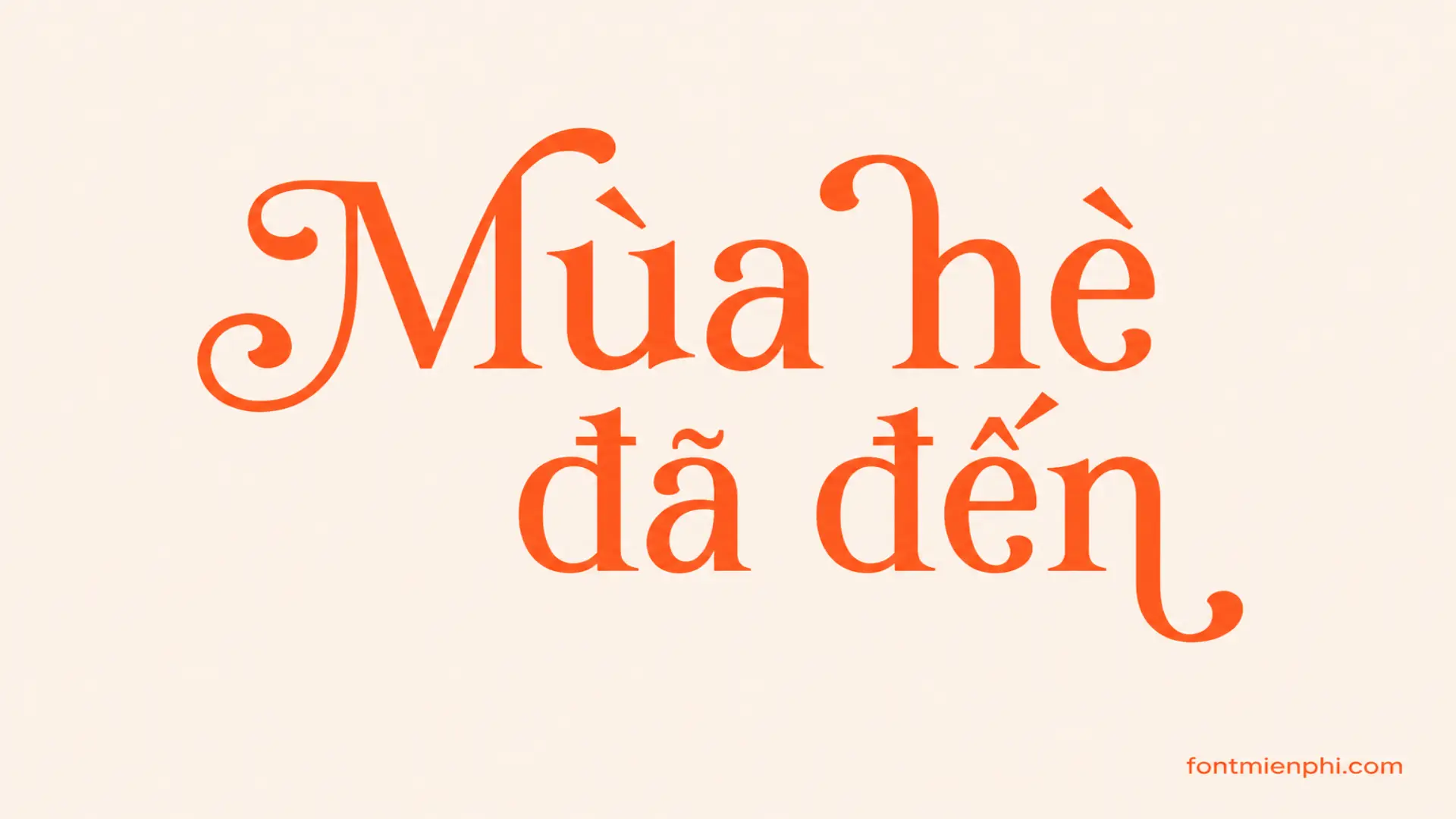
Font Việt hóa 1FTV VIP History Nineties
Tải Font Việt Hóa 1FTV VIP History Nineties – Trở Về Thập Niên 90 Cùng Thiết Kế Đậm Chất Retro
Phong cách Retro/Vintage chưa bao giờ là lỗi thời trong thế giới đồ họa. Nếu bạn đang tìm kiếm một “cỗ máy thời gian” để đưa các tác phẩm của mình quay trở lại không gian hoài niệm, cổ điển đầy chất thơ, thì Font Việt hóa 1FTV VIP History Nineties chính là tấm vé hoàn hảo nhất.
1. Tổng quan về Font 1FTV VIP History Nineties
History Nineties mang trong mình hơi thở của những năm 1990 – thập kỷ giao thoa giữa nét văn hóa mộc mạc và sự bùng nổ của nghệ thuật đại chúng (Pop Art). Cấu trúc của phông chữ này là sự hòa quyện tuyệt vời giữa các đường lượn sóng mềm mại, form chữ dày dặn và những nét cắt dứt khoát mang hơi hướng của các biển hiệu quảng cáo xưa cũ.
Đặc biệt, phiên bản Việt hóa VIP từ 1FTV đã khắc phục hoàn toàn điểm yếu của các font nước ngoài khi gõ tiếng Việt. Toàn bộ các dấu câu (hỏi, ngã, nặng, sắc, huyền) và các ký tự đặc thù (ă, â, đ, ê, ô, ơ, ư) đều được tinh chỉnh thủ công. Dấu câu được đặt ở tỷ lệ hoàn hảo, không làm vỡ bố cục gốc, giúp tổng thể Typography trở nên mượt mà và chuyên nghiệp.
2. Vì sao History Nineties là “Must-have Font” của Designer?
• Đậm đà phong cách Retro: Chỉ cần gõ một dòng text, ấn phẩm của bạn đã lập tức toát lên vẻ hoài cổ, lãng mạn mà không cần lạm dụng quá nhiều hiệu ứng hình ảnh (texture).
• Dễ đọc, nổi bật: Dù mang phong cách Vintage, các ký tự vẫn giữ được sự rõ ràng, tách bạch, đảm bảo khả năng truyền đạt thông điệp xuất sắc (Legibility).
3. Gợi ý ứng dụng Font History Nineties trong thực tế
Sức hút của Font Việt hóa 1FTV VIP History Nineties nằm ở khả năng biến hóa đa dạng trong nhiều dự án mang concept xưa cũ:
🎬 Poster Phim, Âm nhạc & Sự kiện
Đây là lựa chọn “đỉnh của chóp” để làm tiêu đề cho các MV ca nhạc Lofi, nhạc Indie, ảnh bìa Podcast hay poster các bộ phim lấy bối cảnh thập niên cũ, thời kỳ bao cấp.
☕ Branding cho Quán Cafe & Local Brand
Rất nhiều tiệm cà phê phong cách mộc, tiệm may đo, hoặc các thương hiệu thời trang đường phố (Streetwear/Local Brand) ưa chuộng phông chữ này để thiết kế Logo, in ấn bao bì (Packaging) hoặc thiết kế áo thun (T-shirt) cực chất.
📸 Typography cho Nhiếp ảnh & Quotes
Nếu bạn thích chèn những câu Quotes sâu lắng vào các bức ảnh màu phim (Film photography), History Nineties sẽ giúp bức ảnh của bạn trở nên “nghệ” và giàu cảm xúc hơn gấp nhiều lần.